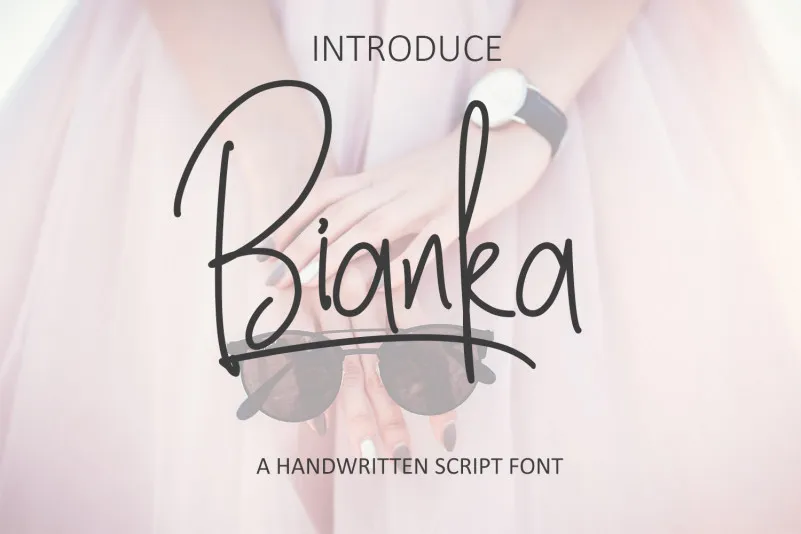
Bianka Font – Download Grátis
A fonte Bianka é perfeita para quem busca uma elegância simples e moderna. Ideal para uso em indústrias como moda ou design de interiores, a Bianka oferece um estilo autêntico com sua versão cuidadosamente escrita à mão cívilizada. Suave mas poderosa, esta fonte monoline contribui significativamente para o estilo e a elegância dos seus projetos. Adaptada ao estilo retrô moderno ou uma revolução minimalista no design de moda, a Bianka é um recurso indispensável para designers que querem dar um toque distintivo aos seus trabalhos. Seja para criar rótulos de embalagens, elementos de logomarca ou até mesmo gráficos para redes sociais, esta fonte proporcionará uma harmonia perfeita, com seu design autêntico e elegante. A azcreativestd trouxe consigo um toque distintivo na criação desta fonte, oferecendo-lhe o melhor em estilo e praticidade.